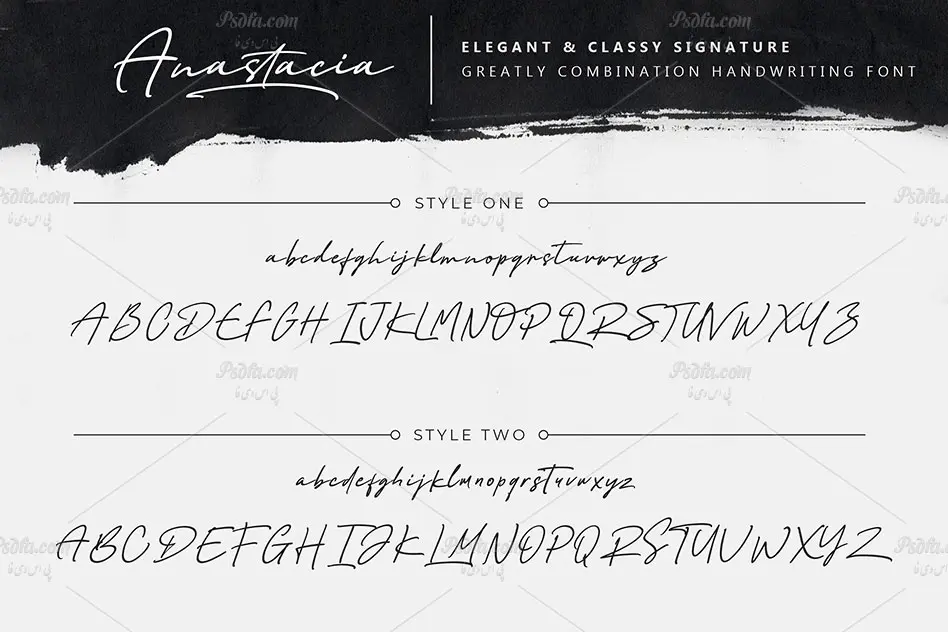
فونت امضاء و دستنویس انگلیسی فوق العاده زیبای Anastacia
فونت امضاء و دستنویس انگلیسی
در این مطلب شاهد فونت امضاء و دستنویس انگلیسی فوق العاده زیبای Anastacia مناسب جهت استفاده در طراحی و گرافیک می باشید. این فونت زیبا در قالب 3 فایل ttf و otf در سایت بارگذاری شده اند که پس از نصب یکی از این دو فرمت در پوشه فونت های سیستم قادر به استفاده از این فونت زیبا در تمام نرم افزارهای گرافیکی و ویرایشگر متن از جمله نرم افزار فتوشاپ ، ایلاستریتور ، پریمیر ، مجموعه نرم افزار آفیس و … خواهید بود. فونت Anastacia در سه طرح و شکل مختلف طراحی و ساخته شده است که می توانید از هر کدام در پروژه های گرافیکی خود استفاده کنید. از این فونت زیبا می توان در طراحی انواع کارت پستال ، کارت عروسی ، طراحی انواع پوستر ، طراحی صفحات وب ، استفاده در صنعت چاپ و … بهره مند شد.
- 3 طراحی مختلف